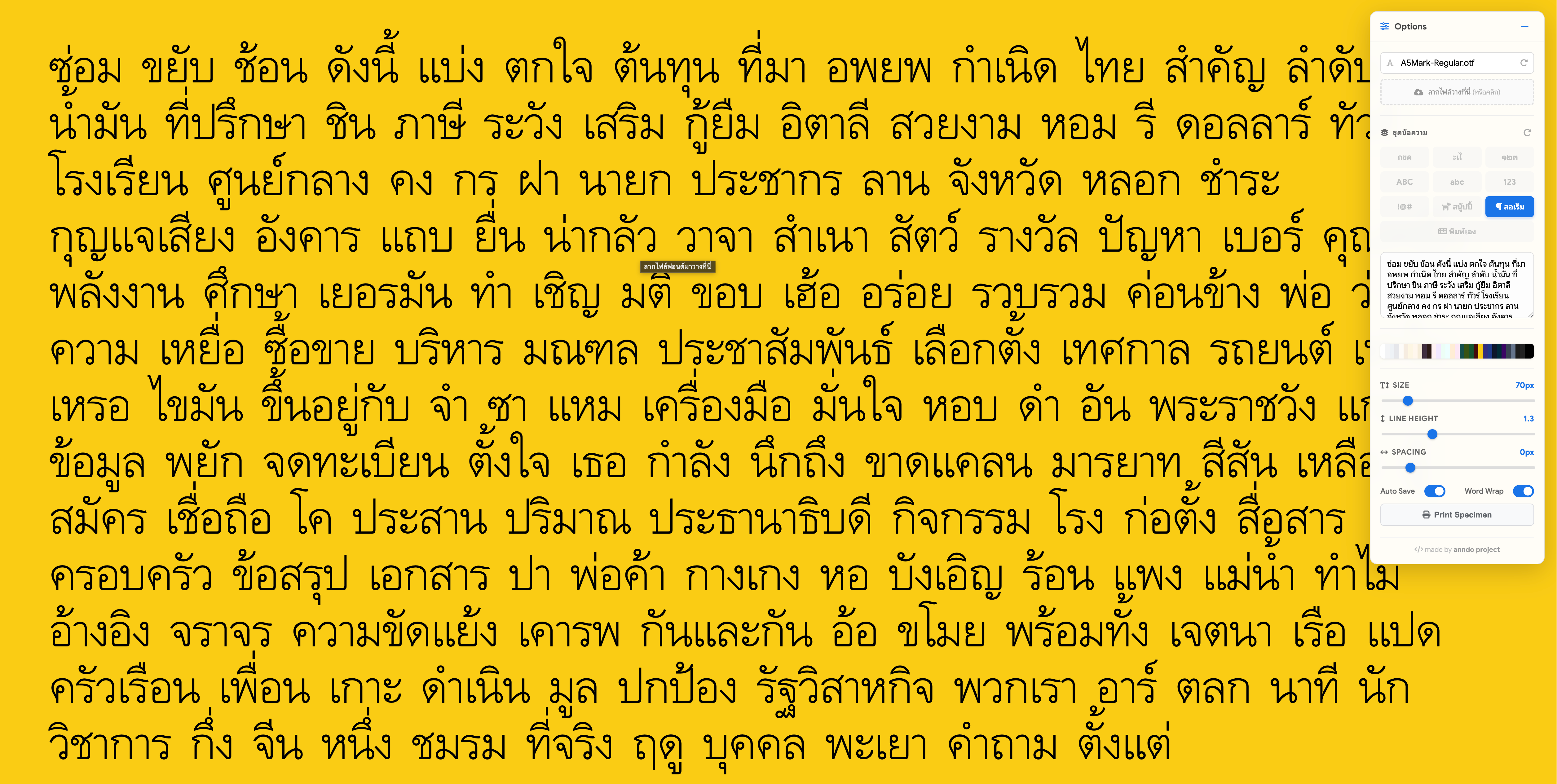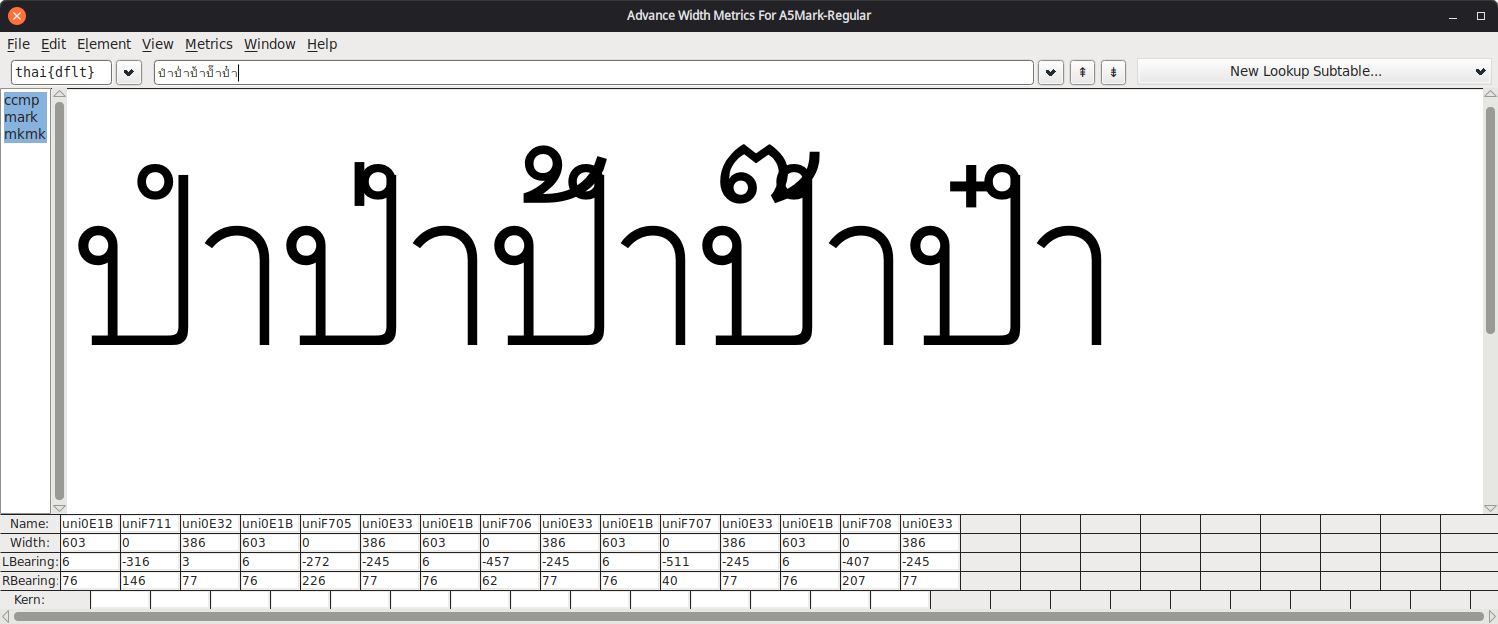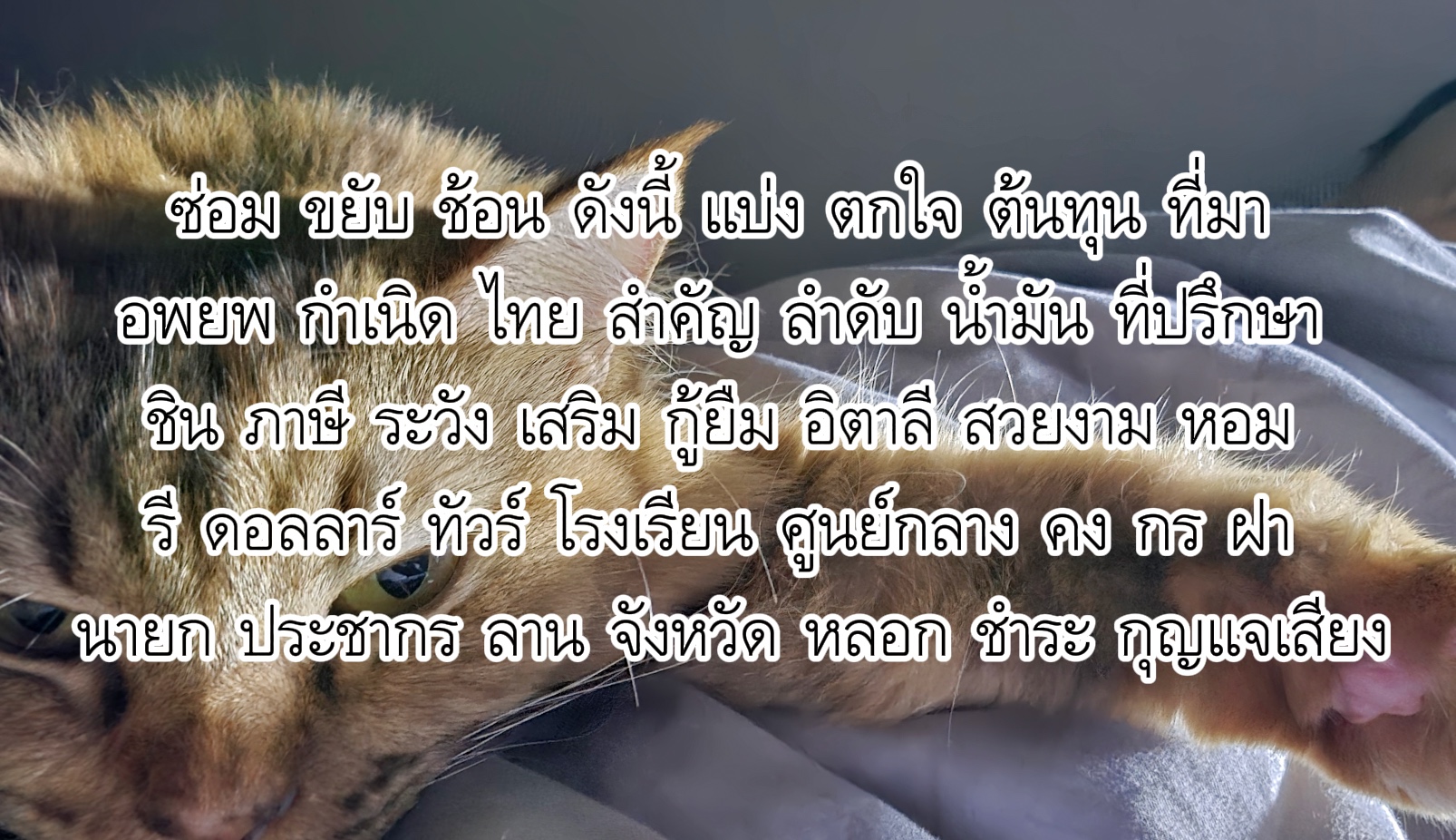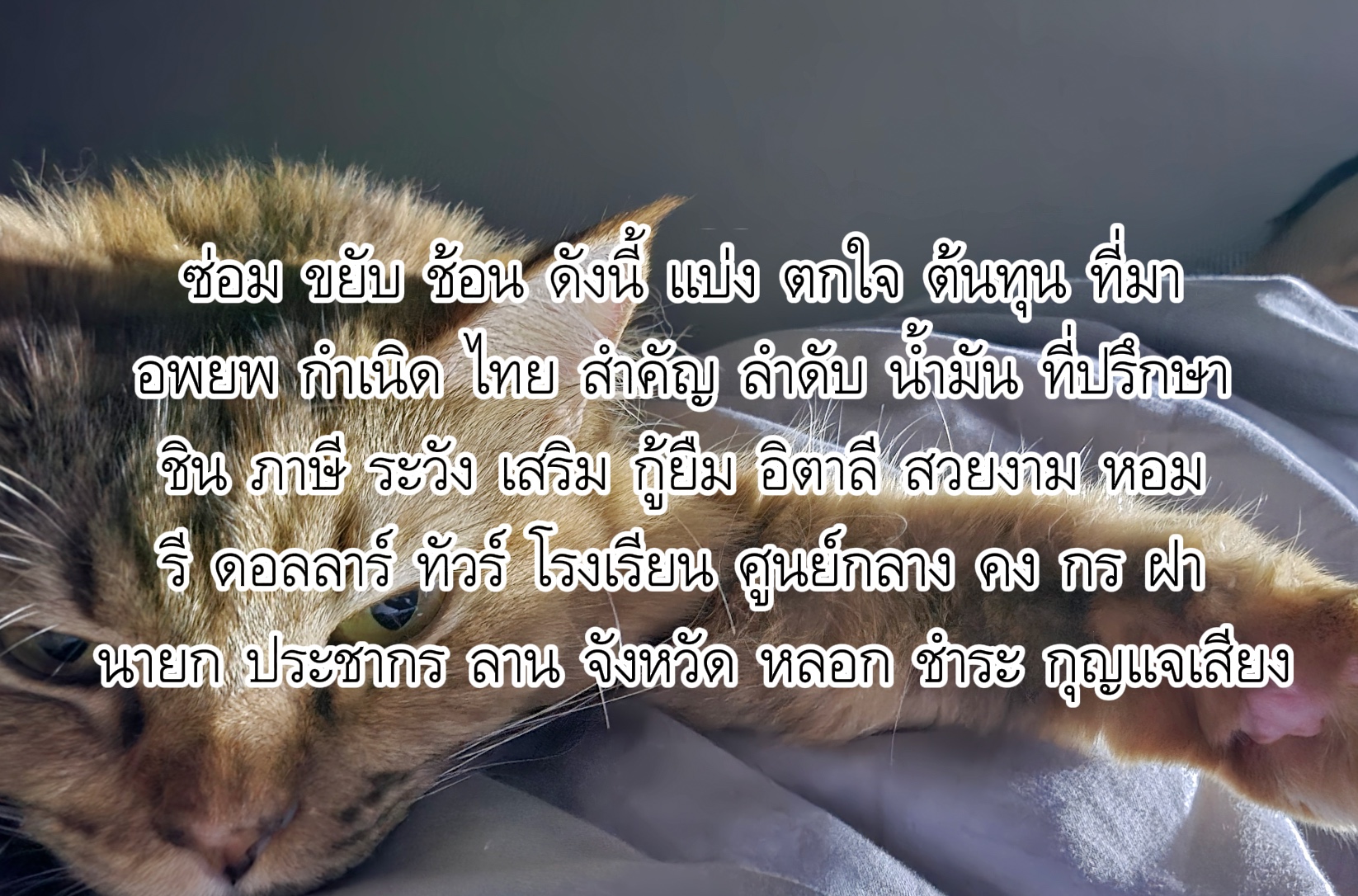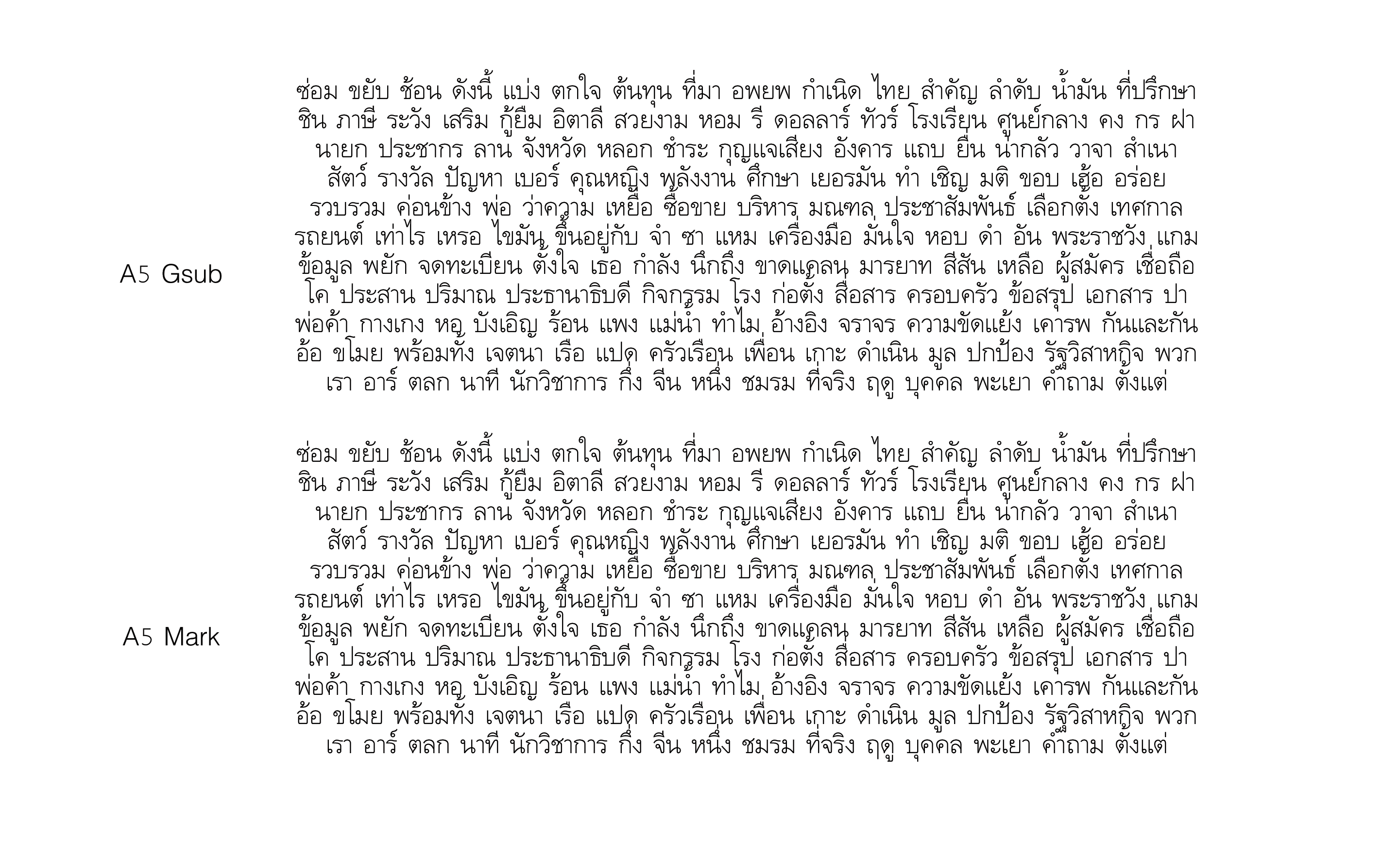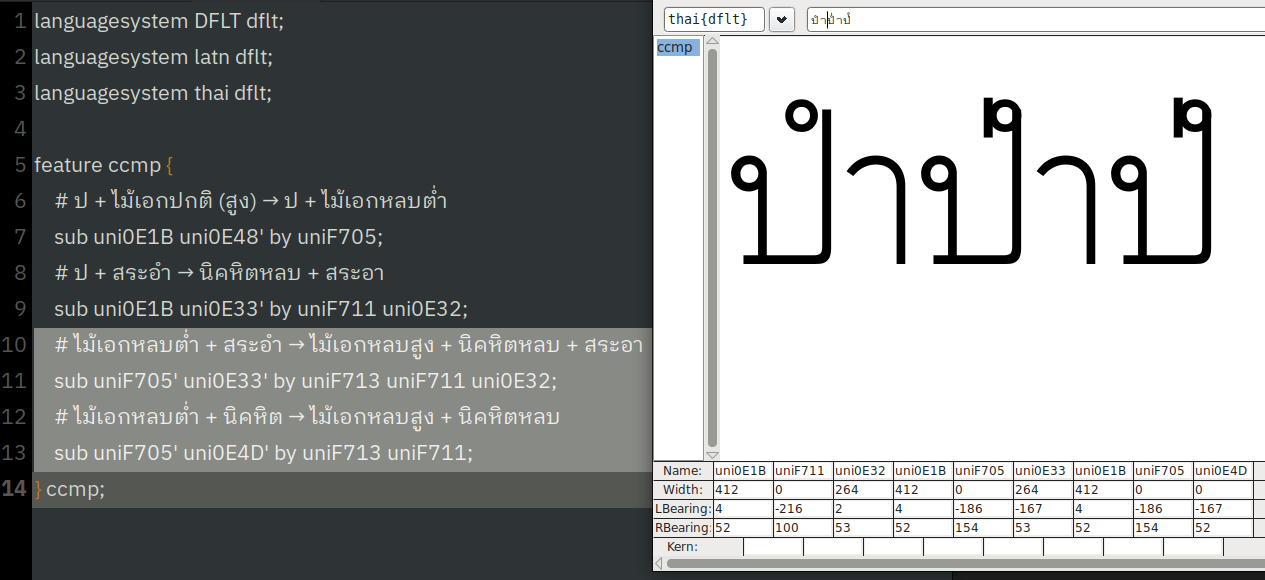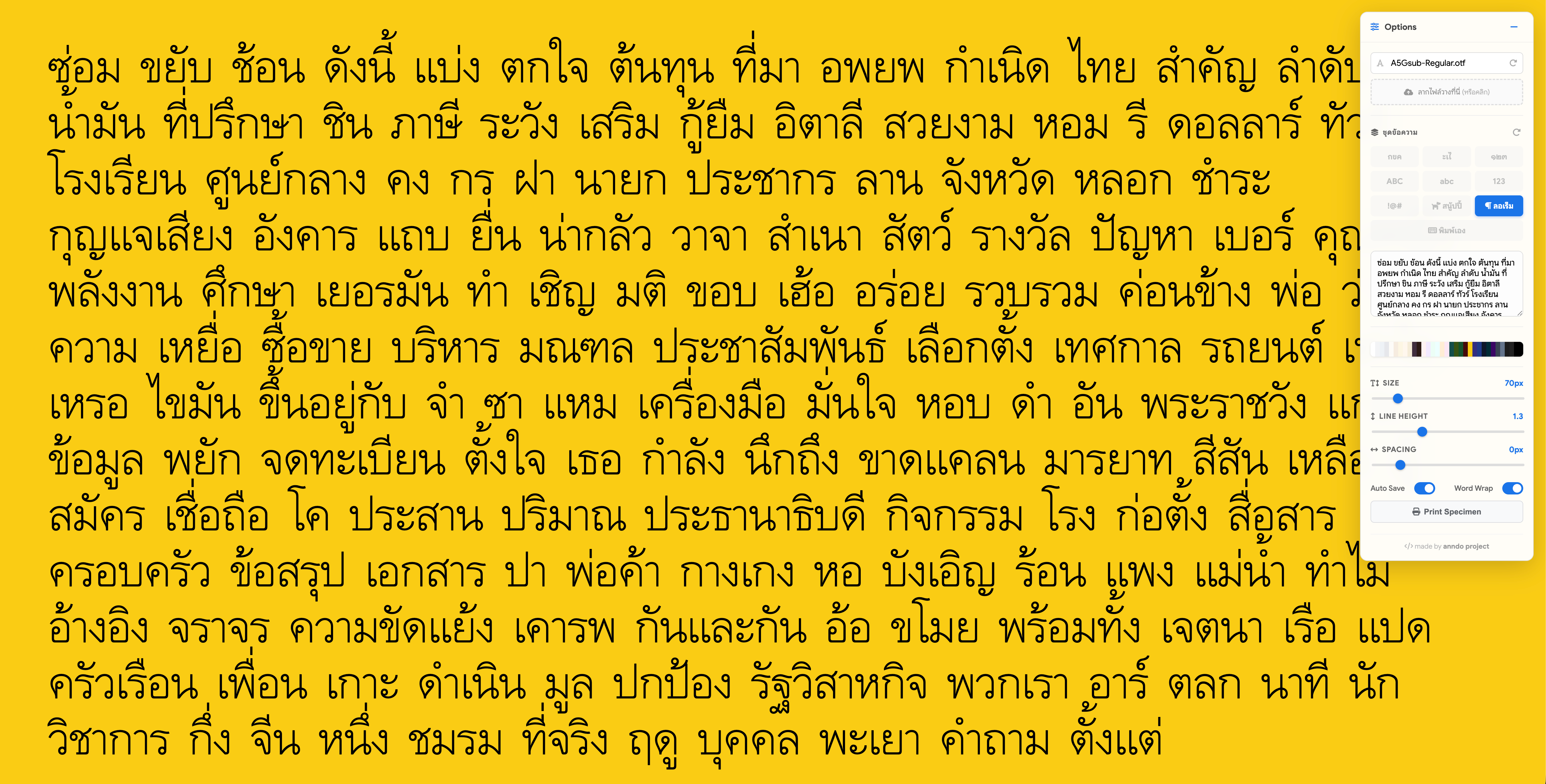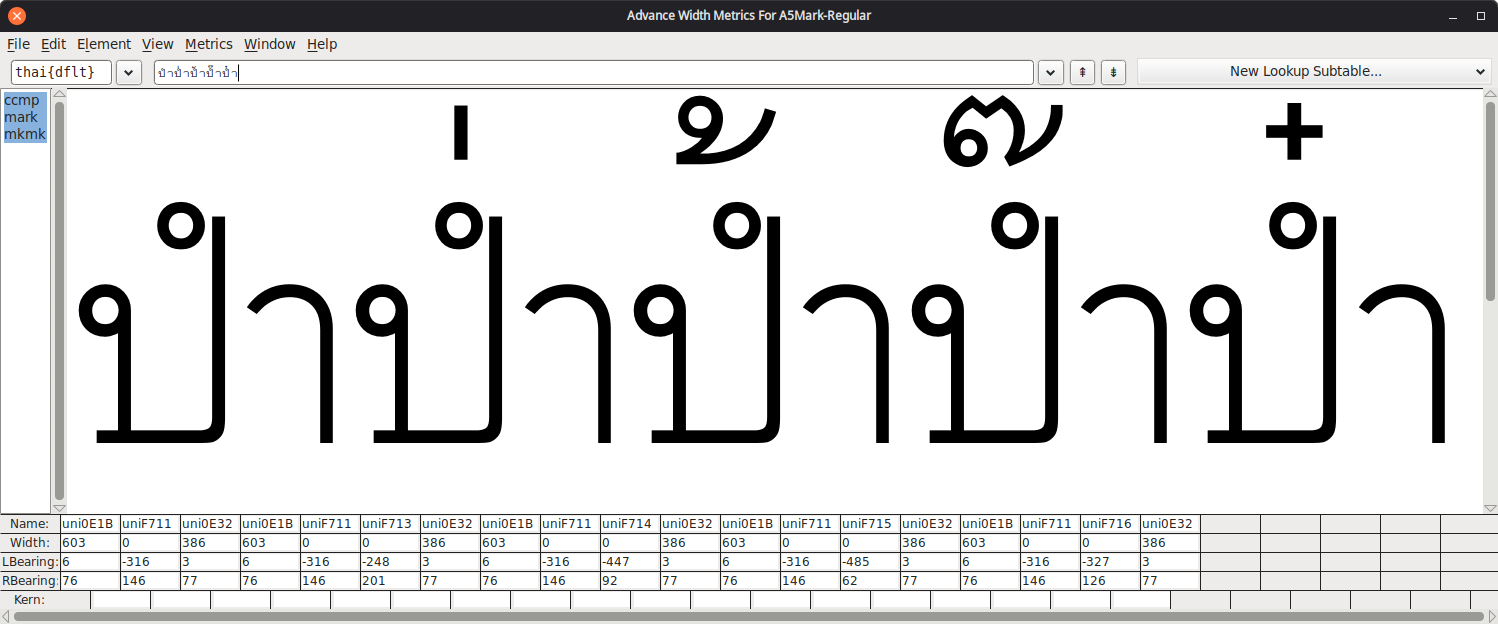
รบกวนเพื่อนสมาชิกช่วยทดสอบฟอนต์หน่อยครับ
ผมเพิ่งเริ่มศึกษาเรื่องการเขียนโปรแกรม OpenType Feature ของฟอนต์ แล้วต้องการรบกวนเพื่อนสมาชิกช่วยทดสอบให้หน่อยครับ
ผมทดสอบบน Linux Mint บนเครื่องตัวเอง มันสามารถทำงานได้ตามที่ออกแบบไว้อย่างสมบูรณ์ แต่ไม่รู้ว่าการทำงานบนระบบอื่น โปรแกรมอื่น จะมีปัญหาอะไรหรือเปล่า ซึ่งถ้ามันสามารถใช้งานได้ไม่มีปัญหา ผมจะได้ใช้เป็นเทมเพลตสำหรับสร้างฟอนต์ต่อๆ ไปน่ะครับ
ฟอนต์ที่ต้องการรบกวนช่วยทดสอบ มี 2 ฟอนต์ ใช้ตัวอักษรจากฟอนต์ JS-Jindara เป็นต้นแบบ ฟอนต์แรกใช้ Gsub เป็นหลัก ฟอนต์สองใช้ Gsub + Mark
ผมใช้ Linux Mint + FontForge ในการ generate font ออกมา ได้ทดสอบบนระบบตัวเองไว้ตามนี้
ไม่รู้ว่าบน Windows, Mac, Mobile และโปรแกรมที่นิยมใช้กันอย่างตระกูล MS Office, Adobe, Canva, CapCut ฯลฯ จะมีปัญหาอะไรหรือเปล่า
ผมใช้แมคครับ
เท่าที่ดู เหมือนจะไม่มีปัญหาเรื่องวรรณยุกต์จม-ลอย หลบหาง ตัวโค้ดน่าจะโอเคล่ะ
พิมพ์ "ป่ำ" นิคหิต ยังทับหาง "ป ฝ ฟ" ครับ
ต้องเพิ่ม script แยกสระอำ ให้เป็น นิคหิต และ สระอา
สอบถามหน่อยครับ คำว่าป่ำ ที่มีปัญหานี่คือ os อะไร โปรแกรมอะไรเหรอครับ
ของผมที่ทดสอบ มันหลบแล้วน่ะครับ
ผมไม่ได้ install font ครับ ทดสอบใน fontforge เลย (เพราะมันตรวจสอบตาม script ที่เขียน ไม่ได้ใช้ความสามารถของ OS)
ในรูปแสดงให้เห็นการ handle สระอำแล้ว แต่สระอำที่มีวรรณยุกต์ ยังไม่สมบูรณ์ครับ
จริงๆไม่ต้องแก้ไขก็ได้ เพราะ โปรแกรม และ OS ส่วนใหญ่ รู้จักภาษาไทย และจัดการเรื่องสระอำให้แล้ว จึงแสดงผลถูกต้อง (จนเรานึกว่าเราเขียน script ครบถ้วนแล้ว)
แล้วก็ไม่ต้องกังวลอะไร font ของ MS ก็สอบด้วยเกณฑ์นี้ไม่ผ่านเหมือนกัน รวมทั้งของ SIPA ด้วย ที่ผ่านจะมีของ NECTEC ฟอนต์ไทย for Linux, ฺฟอนต์Boon, คัดสรร, google (เพราะใช้ script ของคัดสรร)
ของผมทำก็มีทั้งสอบผ่าน และไม่ผ่าน 55 (เพราะเปลี่ยน script ไปเรื่อย ตกๆหล่นๆประจำ)
แปลกจัง ของผมมันแสดงผลได้ปกตินะ
สคริปต์จัดการสระอำหลบหางอยู่ใน GSUB SaraAm ครับ
ภาพตัวอย่างจากเวอร์ชันที่ผมใช้ครับ (2025-10-09)
ผมใช้ FontForge เวอร์ชัน 2025-10-09 บน Linux Mint 22.2 ครับ
ของคุณ uvSOV ใช้เวอร์ชัน 2023 หรือเปล่าครับ
ผมเจอปัญหาเรื่องสคริปต์ไม่ทำงานกับเวอร์ชัน 2023  (ติดตั้งจาก repo) ตอนแรกก็สงสัยว่าเกิดอะไรขึ้น กว่าจะไล่เจอต้นตอปัญหา
อันนี้อาการของเวอร์ชัน 2023 ครับ สคริปต์จัดการเรื่องวรรณยุกต์ มีบางอันที่ไม่ทำงาน
คำถามเพิ่มเติมครับ
คุณ uvSOV ใช้ FontForge ทำงานเป็นหลักใช่ไหมครับ
ผมเจอปัญหาว่าตอนที่จุด anchor (mark / mkmk) มันซ้อนทับอยู่บนจุดหรือเส้นของตัวอักษร (หน้าต่าง Glyph edit)
ผมไม่สามารถคลิกเลือกเพื่อขยับหรือตั้งค่าได้เลย 😓
ตอนนี้ใช้วิธีไปขยับเอาจากหน้า Anchor Control... (จิ้มเลือก Edit Data จากหน้าต่างที่ใช้ตั้งค่า GPOS)
คุณ uvSOV พอจะแนะนำวิธีจิ้มเลือก anchor ตอนมันไปซ้อนกับตัวอักขระได้ไหมครับ
โห!เขาไป version 2025 กันแล้วหรอ ผมยัง 2020 อยู่เลย  :08:
แต่ก็ยังยืนยันนะว่า script ที่เขียนสำหรับจัดการสระอำบน ปฝฟ มันยังไม่ถูกนะ  fontforge ไม่ได้แสดงผลผิดอะไร(ไม่งั้นจะมีฟอนต์ที่แสดงผลถูกต้องได้ยังไง?) ลองกลับไปดูอีกที แอบเฉลยว่า.. logic ไม่ได้ผิด แต่ตัวแปรผิด
หมายเหตุ ยังยืนยันเหมือนกันว่า จะไม่แก้ก็ได้ เพราะ OS จัดการให้แล้ว  ถ้ายังติดใจก็แก้ไข ไม่ติดใจก็ปล่อยผ่านได้ครับ
อ๋อ ก็คือมันไม่ได้ถูกตามหลักวิธีเป๊ะๆ
แต่ตอนนี้การแสดงผลมันถูก OS / โปรแกรมเข็นให้ จนฝั่งผู้ใช้รู้สึกปกติใช่ไหมครับ
ผมใช้ฟอนต์เก่า ที่ใช้ผังฟอนต์ที่ยังแยกวรรณยุกต์เป็น 4 ชุด 4 ตำแหน่ง + สระหลบหาง และไม่มีการเขียน script ควบคุมใดๆ ทั้งสิ้น
ตัว Linux และ LibreOffice สามารถแสดงเรื่องตำแหน่งสระและวรรณยุกต์ได้อย่างถูกต้องด้วยเอนจิน HarfBuzz
ผมเลยคิดว่าตัว os มันคงจัดการให้อัตโนมัติ (เหมือนสมัยพวก Windows XP + Office XP)
แต่พอได้ไปใช้งานกับ Windows 10/11 และ MS Office (รุ่นอะไรซักรุ่นนี่แหละ) ปรากฏว่าวรรณยุกต์ลอยเท้งเต้ง ไม่มีการจัดการอะไรให้ ถึงได้รู้ว่า Win + Office รุ่นใหม่ ไม่ได้ทำเรื่องพวกนี้ให้แล้ว
ถ้าเจอ ป + นิคหิต ให้เปลี่ยนเป็น นิคหิตหลบ อันนี้ผ่าน (9)
แต่พอไปถึงบรรทัดตรวจสอบ ไม้เอกหลบ + นิคหิต ไม่ทำงาน (13)
เลยไม่เข้าใจว่าจะต้องจัดการกับมันแบบไหน
เพราะคำสั่งแบบนี้ สามารถทำงานได้กับ FontForge เวอร์ชั่น 2025
ผมเลยเข้าใจว่าน่าจะเป็น bug ของโปรแกรม FontForge
ไปไล่ดูการทำงานของ FontUni-B กับ Boon ถ้าผมเข้าใจไม่ผิดก็คือ
- FontUni-B ใช้วิธีสร้าง Glyph สำหรับสระอำหลบหางขึ้นมาใหม่อีกตัว และนิคหิตในตำแหน่งหลบอีก 2 ตัว (รวมของเดิมเป็น 4 ตำแหน่ง)
- Boon ใช้วิธีกำหนด mark / mkmk เพื่อจัดการตำแหน่งนิคหิต